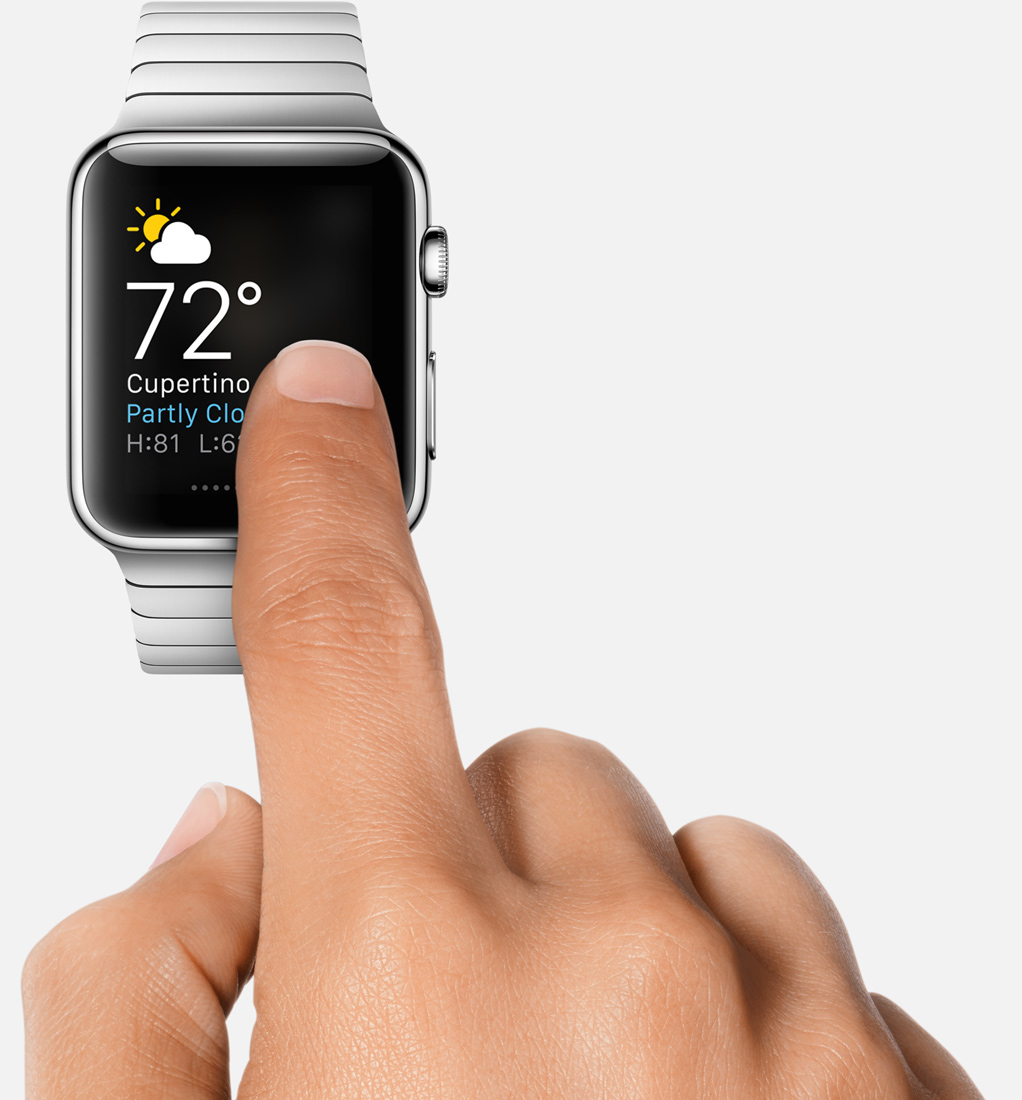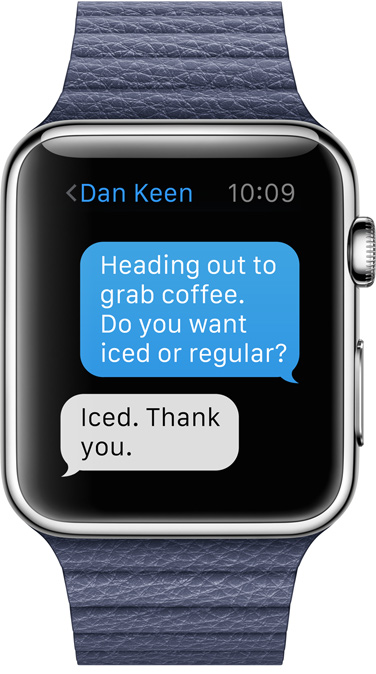
Apple Watch sfrutta un font creato ad hoc
Il nuovo Apple Watch sfrutta un nuovo font creato ad hoc per il nuovo schermo Retina, un carattere che ricorda “Roboto”, font che Google usa per Android. Ne parla The Verge, spiegando che il carattere è “ottimizzato per la leggibilità” del piccolo display. Apple evidenzia che il nuovo font è ben leggibile a distanza di braccio, importante per leggere notifiche, eventi, messaggi e, a colpo d’occhio, le informazioni.
Anche per il futuro OS X 10.10 Yosemite Apple ha adottato un font di sistema aggiornato che dovrebbe migliorare la leggibilità (anziché il Lucida Grande usato sinora, si passa all’Helvetica Neue).